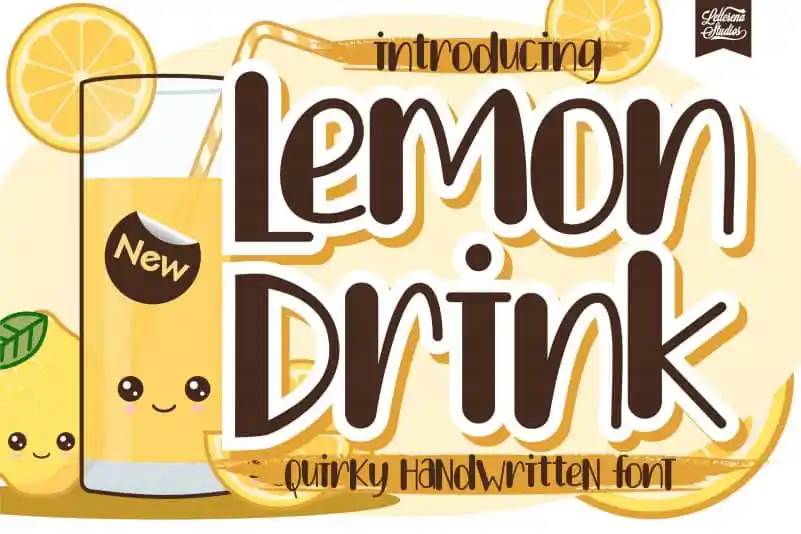
Lemon Drink Display Font – Download Grátis
A Lemon Drink Display Font é uma seleção especial para aqueles que adoram criar visualmente inovadores e divertidos. Desenhada pelo designer letterenastudios, ela traz um toque único de brasilidade através das formas levementes e alegres. Este font é perfeito para incorporar em projetos criativos, como logotipos, rótulos de embalagens ou qualquer outro elemento visual que busque entregar uma pegada descontraída com graça. Apenas adicione esta fonte a seus projetos e observe como ela transforma suas ideias em algo realmente vibrante e único. Lemon Drink Display Font é mais do que apenas um tipo de fonte; ele é um atalho para fazer seu trabalho brilhar ainda mais.